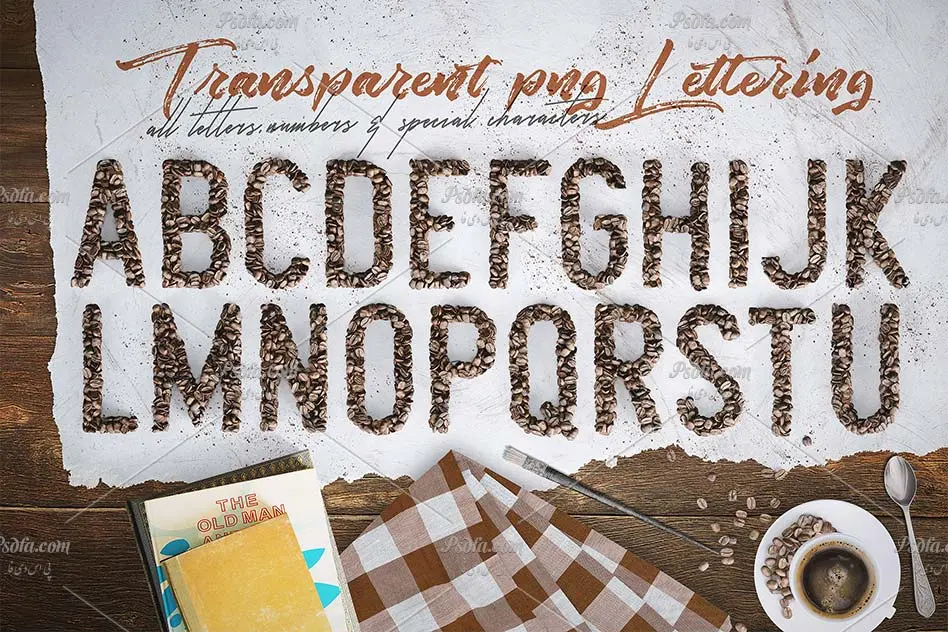
حروف انگلیسی با افکت دانه های قهوه به همراه فونت دانه های قهوه
حروف انگلیسی با افکت دانه های قهوه
در این مطلب شاهد مجموعه تصاویر کلیپ آرت حروف انگلیسی با افکت دانه های قهوه به همراه فونت دانه های قهوه مناسب جهت استفاده در طرح های گرافیکی می باشید. این مجموعه شامل تمام کاراکترهای های حروف انگلیسی به همراه بک گراند و تکسچر چوب و قهوه است که در قالب فایل های png و jpg بر روی سایت بارگذاری شده اند. شما با از کنار هم قرار دادن این حروف و کاراکترها می توانید جملاتی با افکت دانه های قهوه ایجاد کرده و از آن ها در طرح های گرافیکی خود استفاده کنید. البته فونت این کاراکترها نیز به صورت svg در مجموعه موجود بوده که با نصب آن در پوشه فونت های سیستم قادر به استفاده از آن در نرم افزار فتوشاپ خواهید بود و می توانید متون خود را با این افکت زیبا تایپ کنید. تصاویر از کیفیت بالایی برخوردار بوده و همگی مناسب جهت ایجاد طرح هایی با رزولوشن بالا می باشند. از این مجموعه تصویر کلیپ آرت می توانید در طراحی انواع پوستر ، بنر ، تراکت ، بروشور و دیگر طرح های گرافیکی ویژه کافه ها استفاده کنید.